บนพื้นน้ำเงินที่ไล่สีเหมือนสกรีนเซฟเวอร์ปี 1998 มีข้อความสามบรรทัดเขียนว่า YES I HAVE TRIED SPAGHETTI แค่นั้น ไม่มีรูป ไม่มีคำอธิบาย ไม่มีอะไรบอกว่าใครพูดกับใคร และพอยืนดูนานเข้าเราก็เริ่มคิดว่าประโยคนี้มันตอบคำถามอะไรอยู่
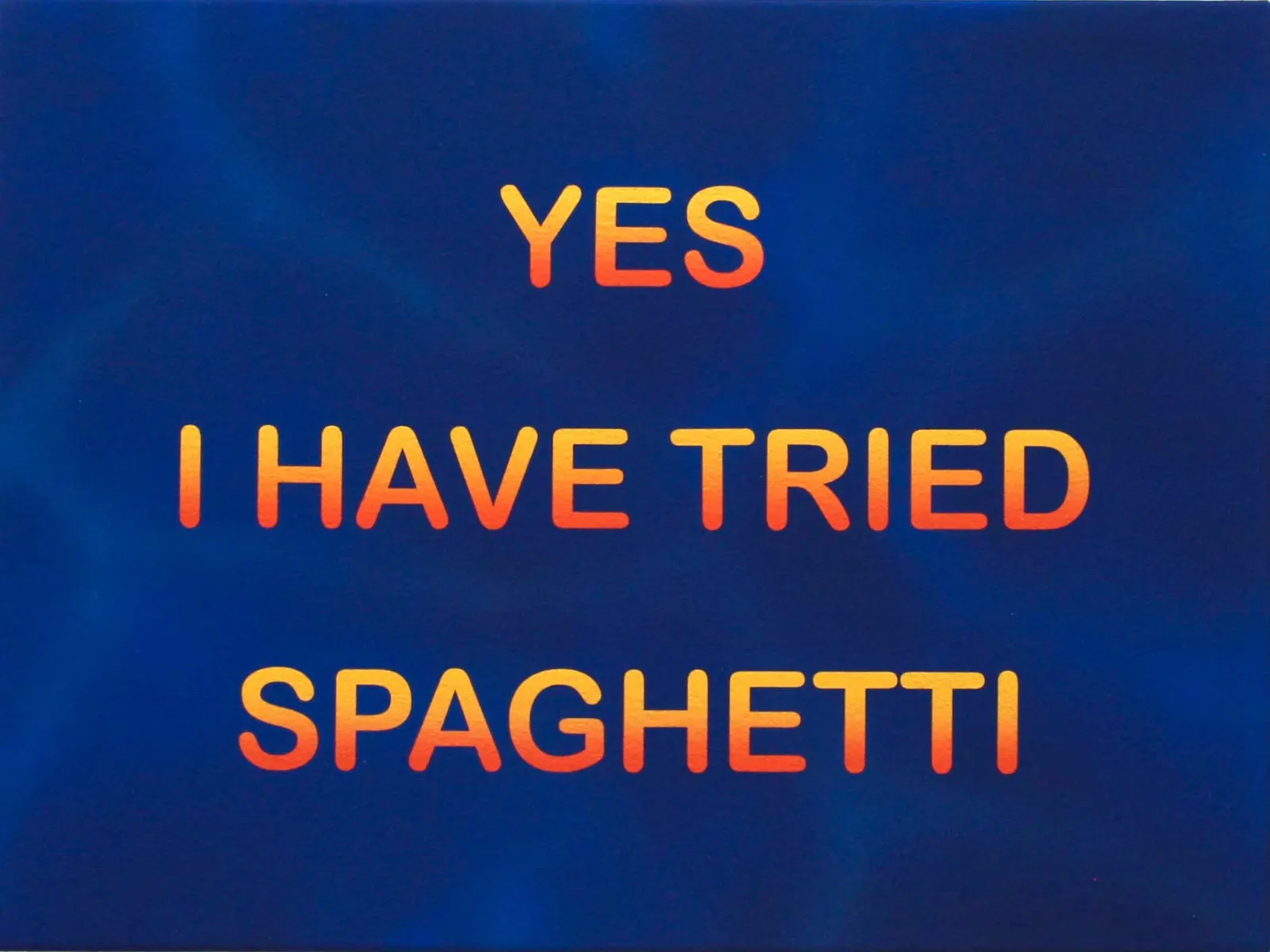
Hunter Harvey ทำงานอยู่ที่ลอสแอนเจลิส เมื่อก่อนเขาวาดภาพมีตัวละครมีฉาก เคยหยิบตัวการ์ตูนอย่างมนุษย์หินฟลินท์สโตนมาใช้ด้วย แล้ววันหนึ่งก็รู้สึกว่าวิธีนั้นมันตันแล้ว เลยตัดทุกอย่างออกจนเหลือแค่ตัวหนังสือ
เก็บประโยคจากบนถนน
เขาบอกไว้ตรง ๆ ว่าเขาเก็บข้อความมาจากทุกที่ ป้ายที่เห็นตอนขับรถ บทสนทนาที่ได้ยินผ่านหูบนถนนในแอลเอ คนเมาในงานปาร์ตี้ และทีวี
เงื่อนไขของประโยคที่เขาเลือกคือต้องสั้น และต้องกำกวมพอที่เราจะแยกไม่ออกว่าคนพูดกำลังพูดจริงหรือพูดเล่น HORSE MONEY สองคำนี้ไม่ได้บอกอะไรเลย แต่มันก็ฟังดูเหมือนเคยผ่านหูมาก่อน
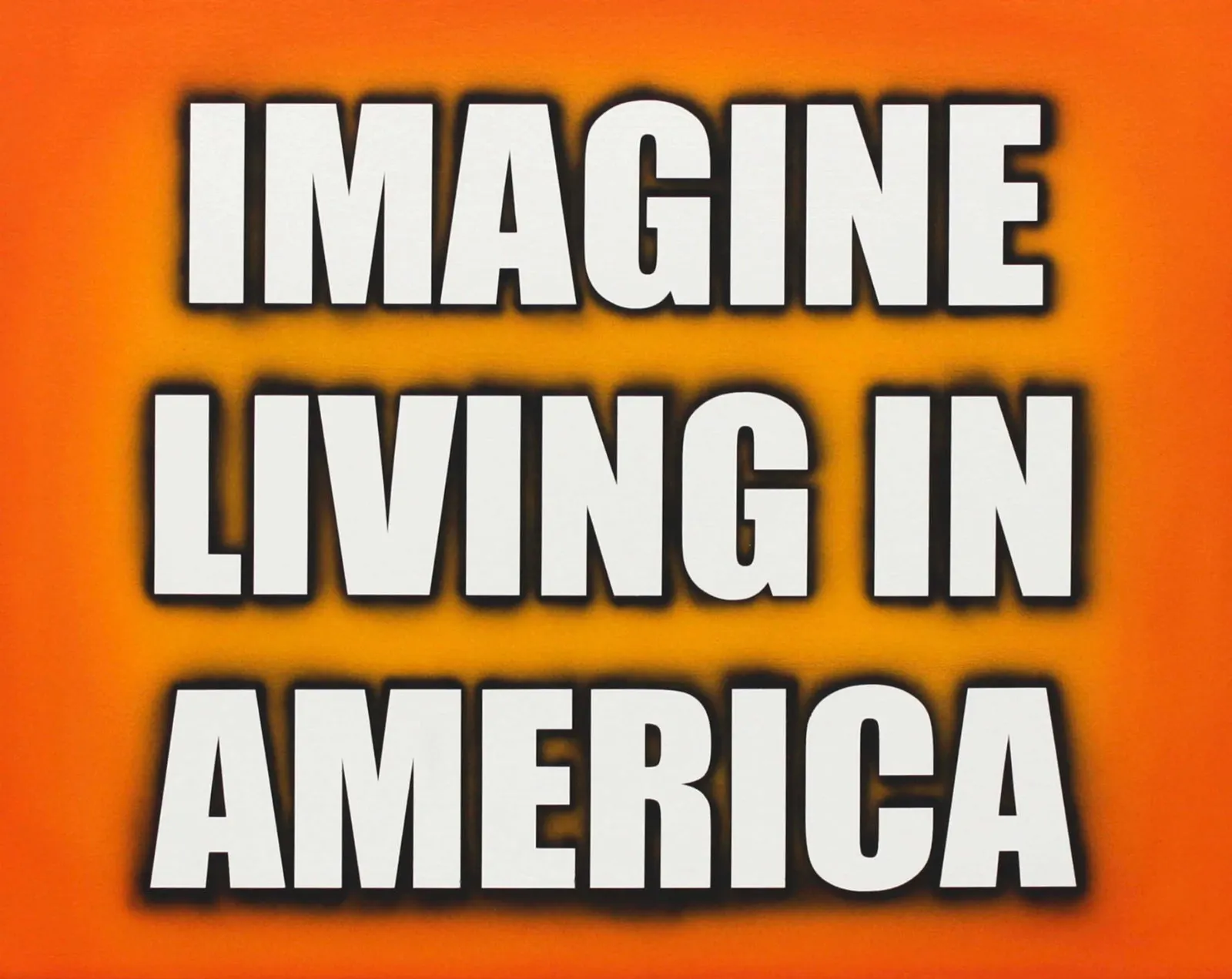
ฟอนต์คือคนพูด
ส่วนที่เราว่าเป็นหัวใจของงานชุดนี้คือเขาคิดเรื่องฟอนต์จริงจังมาก เขาอธิบายว่า Helvetica ให้ความรู้สึกน่าเชื่อถือและมีอำนาจ ส่วน Impact นั้นหนาแน่น ไม่ขอโทษใคร และเอาจริงกับมันยากกว่า แล้วสรุปไว้สั้น ๆ ว่า the typeface becomes part of the message
ลองเอาประโยค IMAGINE LIVING IN AMERICA ไปใส่ในฟอนต์เซริฟบาง ๆ บนการ์ดเชิญ แล้วเทียบกับที่เขาทำ คือตัวหนาทึบมีเงาฟุ้งบนพื้นส้ม ประโยคเดียวกันแต่คนพูดคนละคนกันเลย
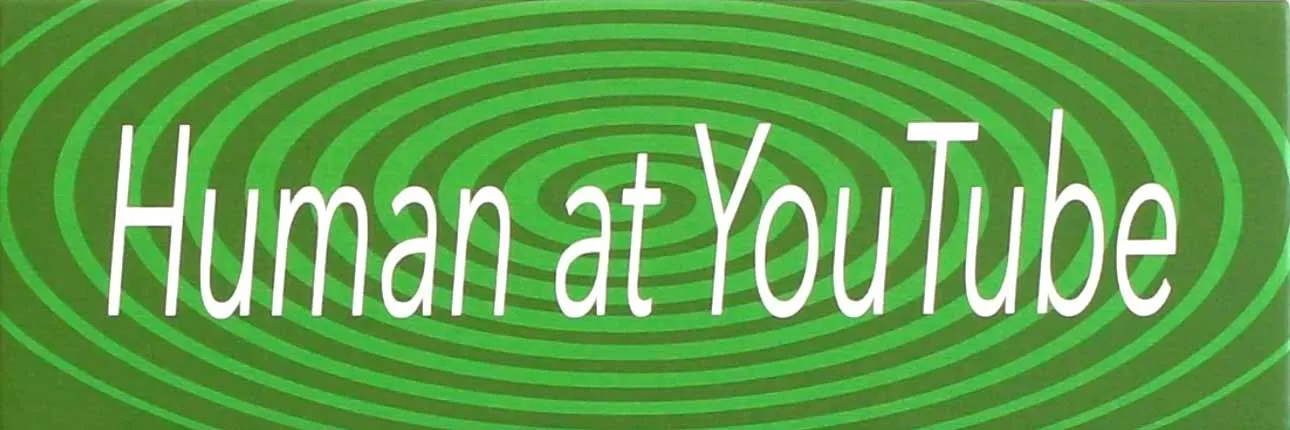
คลังอ้างอิงของเขาเป็นของที่คนวัยทำงานตอนนี้โตมากับมันหมด ฟอนต์ในสไลด์พาวเวอร์พอยต์รุ่นเก่า กรอบวงรีไล่สีแบบเวิร์ดอาร์ต โฆษณาต่อต้านการละเมิดลิขสิทธิ์ที่ขึ้นก่อนหนังแผ่น และสติกเกอร์ติดท้ายรถ
เขาวาดมันขึ้นใหม่ทั้งหมดด้วยมือ ใช้สีฟลาชซึ่งเป็นสีไวนิลที่สดจัดแต่แห้งแล้วด้าน ร่วมกับแอร์บรัชและการปิดกั้นด้วยเทป แปลว่าเงาฟุ้ง ๆ ที่ดูเหมือนเอฟเฟกต์ในโปรแกรม จริง ๆ แล้วเกิดจากการพ่นทีละชั้น
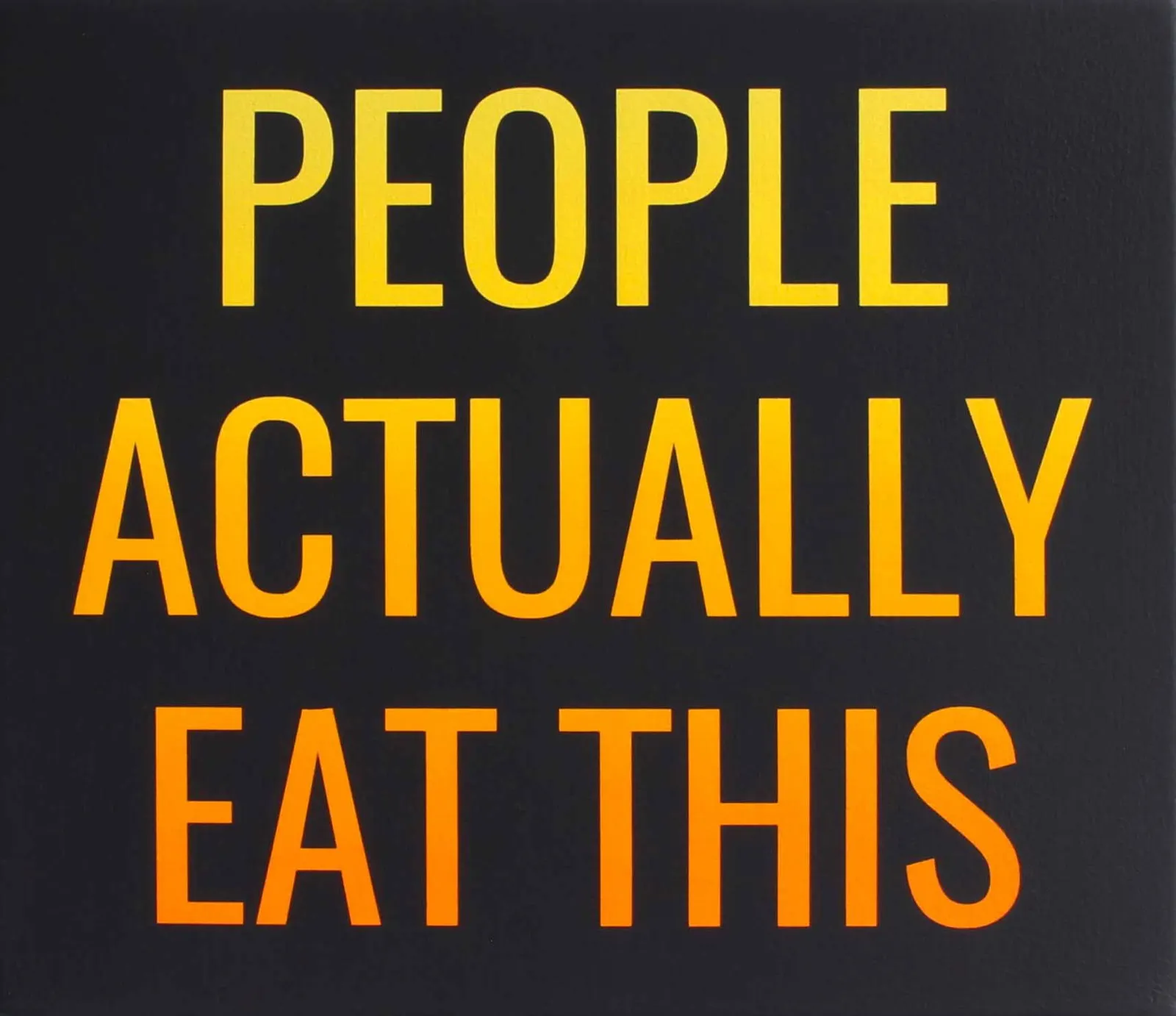
เรื่องที่ซ่อนอยู่ใต้มุก
พอดูหลาย ๆ ชิ้นต่อกันจะเห็นว่ามันไม่ได้ตลกอย่างเดียว ชิ้นหนึ่งเขียนว่า THIS USED TO BE A GAY BAR บนดวงไฟสีส้มแดงที่ค่อย ๆ จางออกไปทางขอบ อ่านผ่าน ๆ เหมือนคำบอกทาง แต่มันคือประโยคที่พูดถึงพื้นที่ที่หายไปแล้วจากเมือง
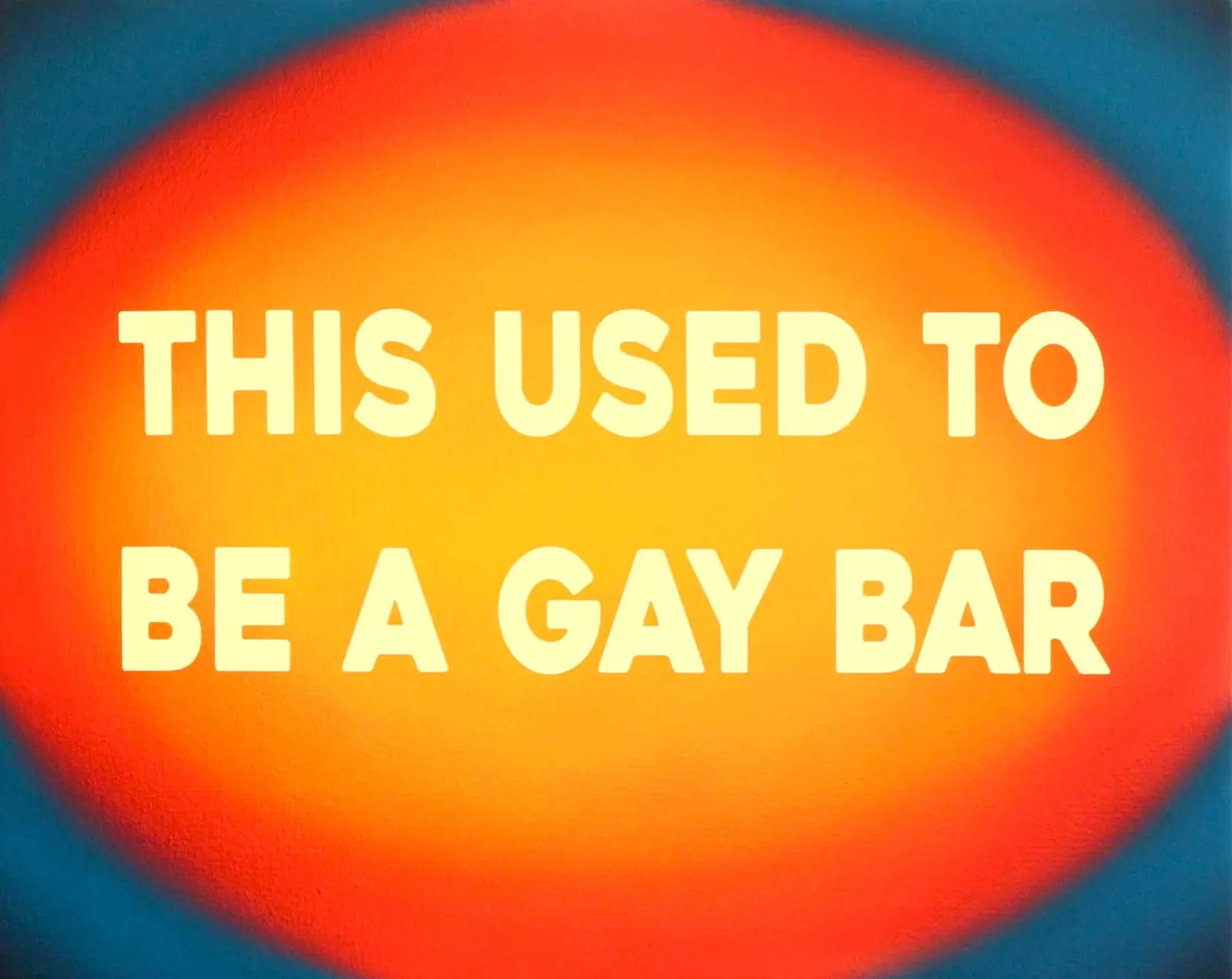
อีกชิ้นเขียนว่า IT'S PRONOUNCED WILSHIRE ซึ่งเป็นชื่อถนนสายหลักของแอลเอที่คนต่างถิ่นออกเสียงผิดประจำ ประโยคสั้นแบบนี้แยกคนที่อยู่มานานกับคนเพิ่งย้ายมาออกจากกันได้ในคำเดียว
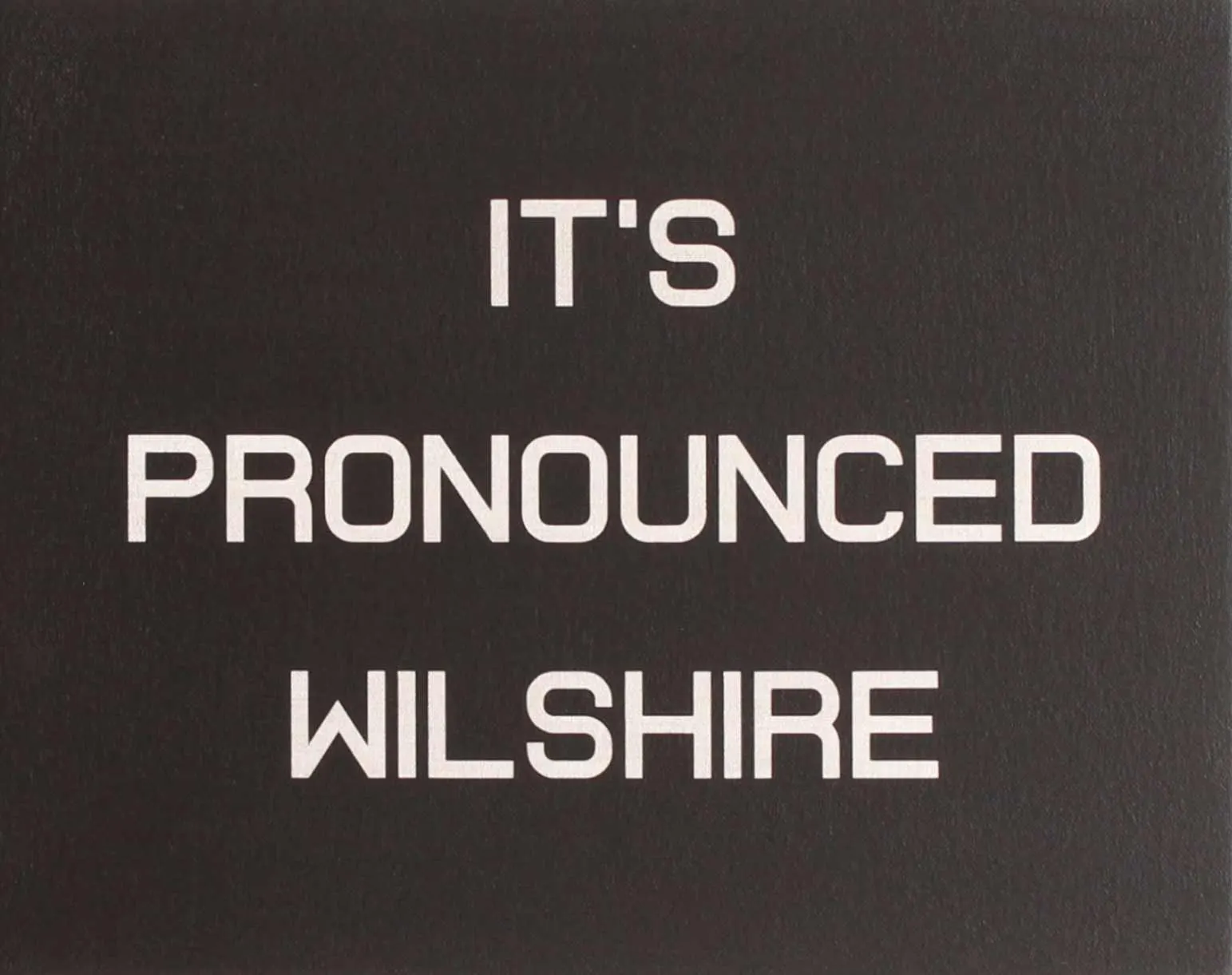
มีชิ้นที่ขำร้ายกว่านั้นอีก คือ I LOVE HAPPY HOURS ที่เขาวางบนสี่เหลี่ยมซ้อนกันเป็นชั้น ๆ สีส้มไล่เข้าไปหาแดง ใครที่เคยเรียนทฤษฎีสีจะเห็นทันทีว่านี่คือการล้อภาพชุดสี่เหลี่ยมซ้อนของ Josef Albers ที่โรงเรียนศิลปะทั่วโลกใช้สอนเรื่องสีมาหลายสิบปี เอางานที่ศักดิ์สิทธิ์ที่สุดในห้องเรียนมาแปะคำว่าชอบชั่วโมงลดราคาเหล้า
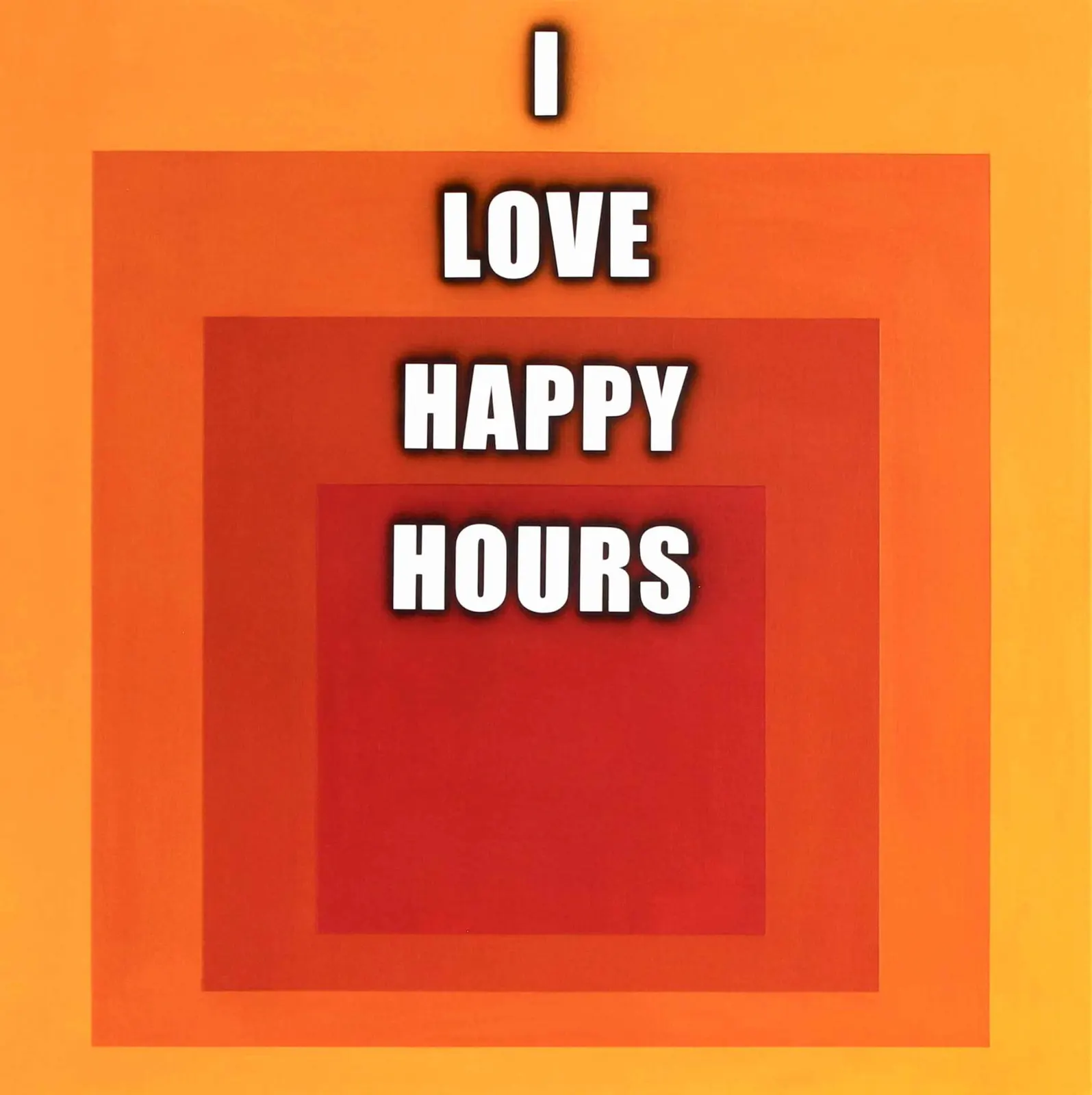
ในแง่นี้เขาทำงานคล้ายกับคนที่เก็บตัวอักษรจากป้ายร้านมาทำฟอนต์อย่าง Greenpoint Sans คือเดินเก็บของที่คนเดินผ่านทุกวันแล้วไม่เคยมอง ต่างกันตรงที่คนหนึ่งเก็บรูปทรงของตัวอักษร อีกคนเก็บน้ำเสียงของคนพูด
อีกชั้นที่ทำให้งานชุดนี้ไม่ใช่แค่มุกคือแรงที่ลงไปกับมัน ข้อความพวกนี้ถ้าอยู่บนโพสต์ในฟีด เราเลื่อนผ่านในสองวินาที แต่การที่มีคนยอมพ่นสีทีละชั้น ติดเทป ลอกเทป รอแห้ง เพื่อให้ได้เงาฟุ้งที่โปรแกรมทำเสร็จในสามคลิก มันเปลี่ยนความหมายของประโยคไปเลย เพราะเวลาที่ใช้ไปกลายเป็นส่วนหนึ่งของเรื่อง
สิ่งที่ค้างอยู่หลังจากดูจบคือ ประโยคพวกนี้ไม่มีใครเป็นเจ้าของ มันลอยอยู่ในอากาศของเมือง แล้ววันหนึ่งก็มีคนหยิบมันขึ้นมาแขวนไว้บนผนัง